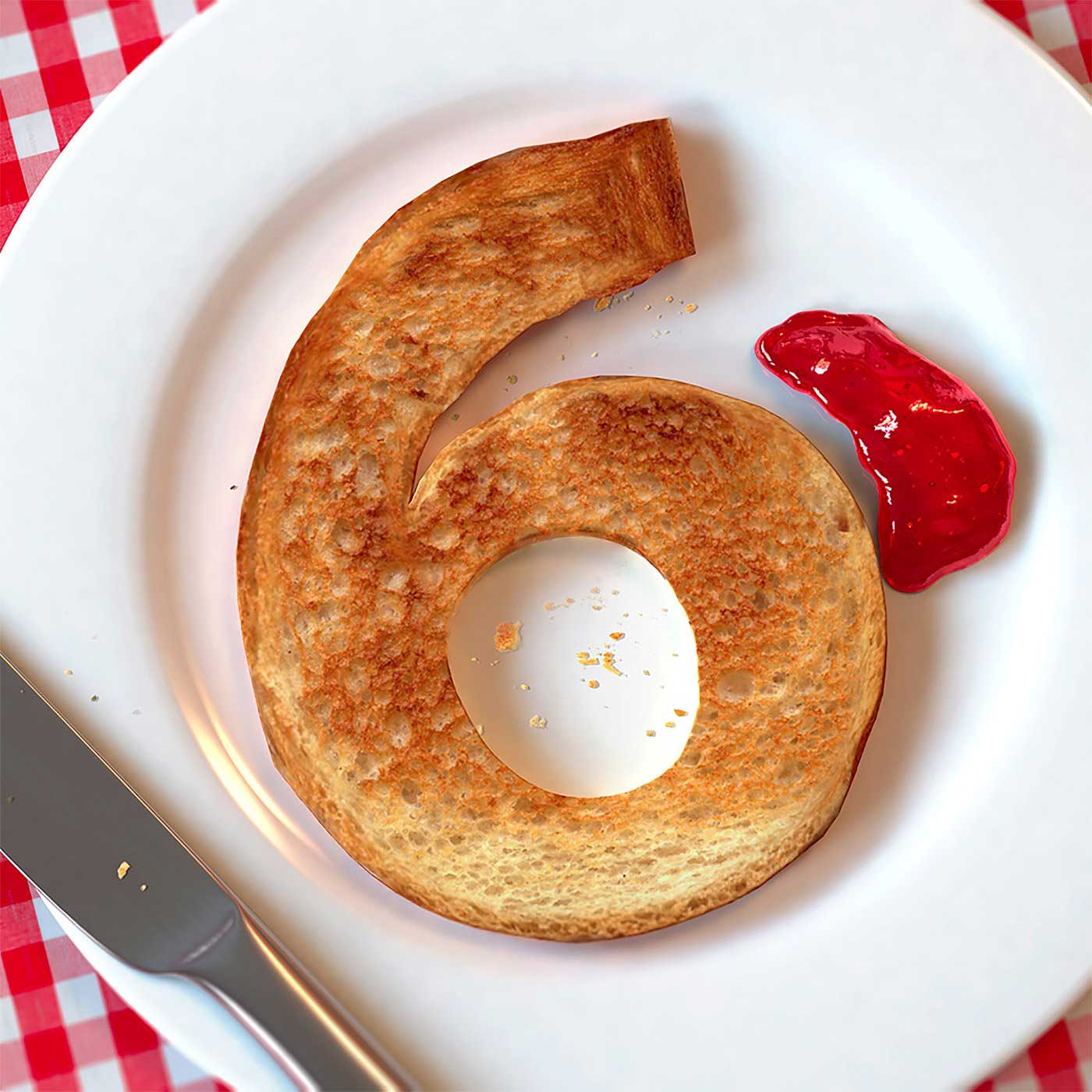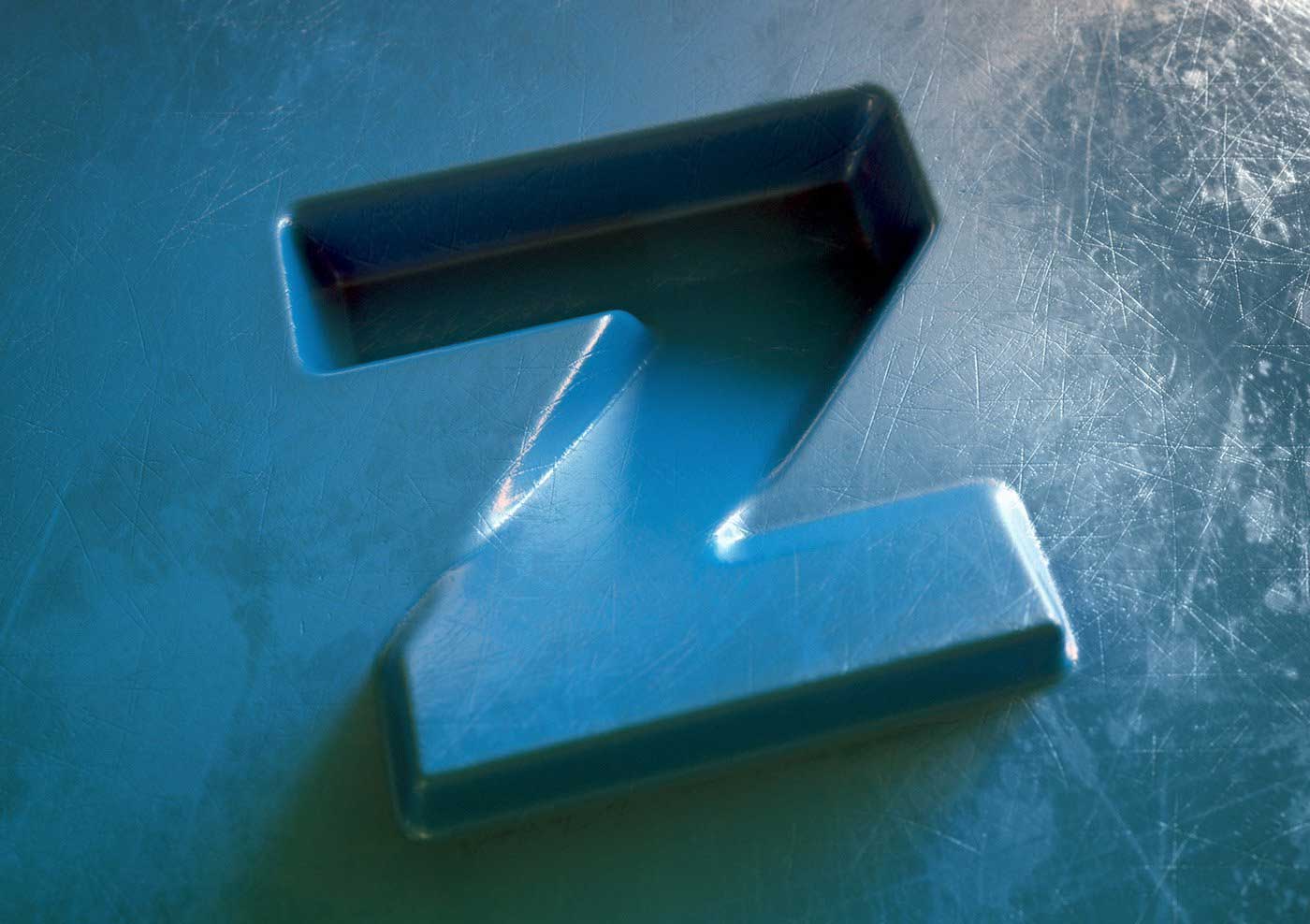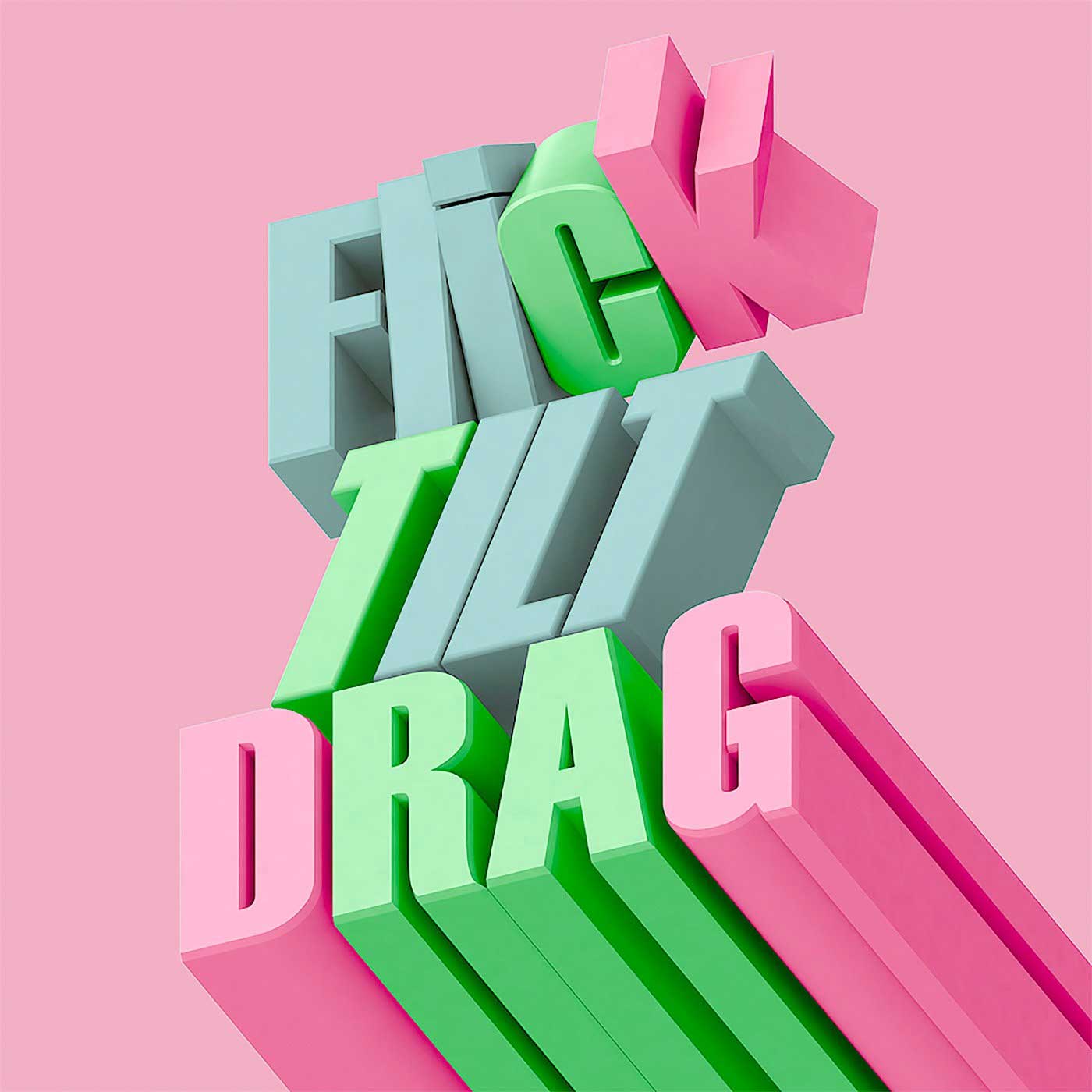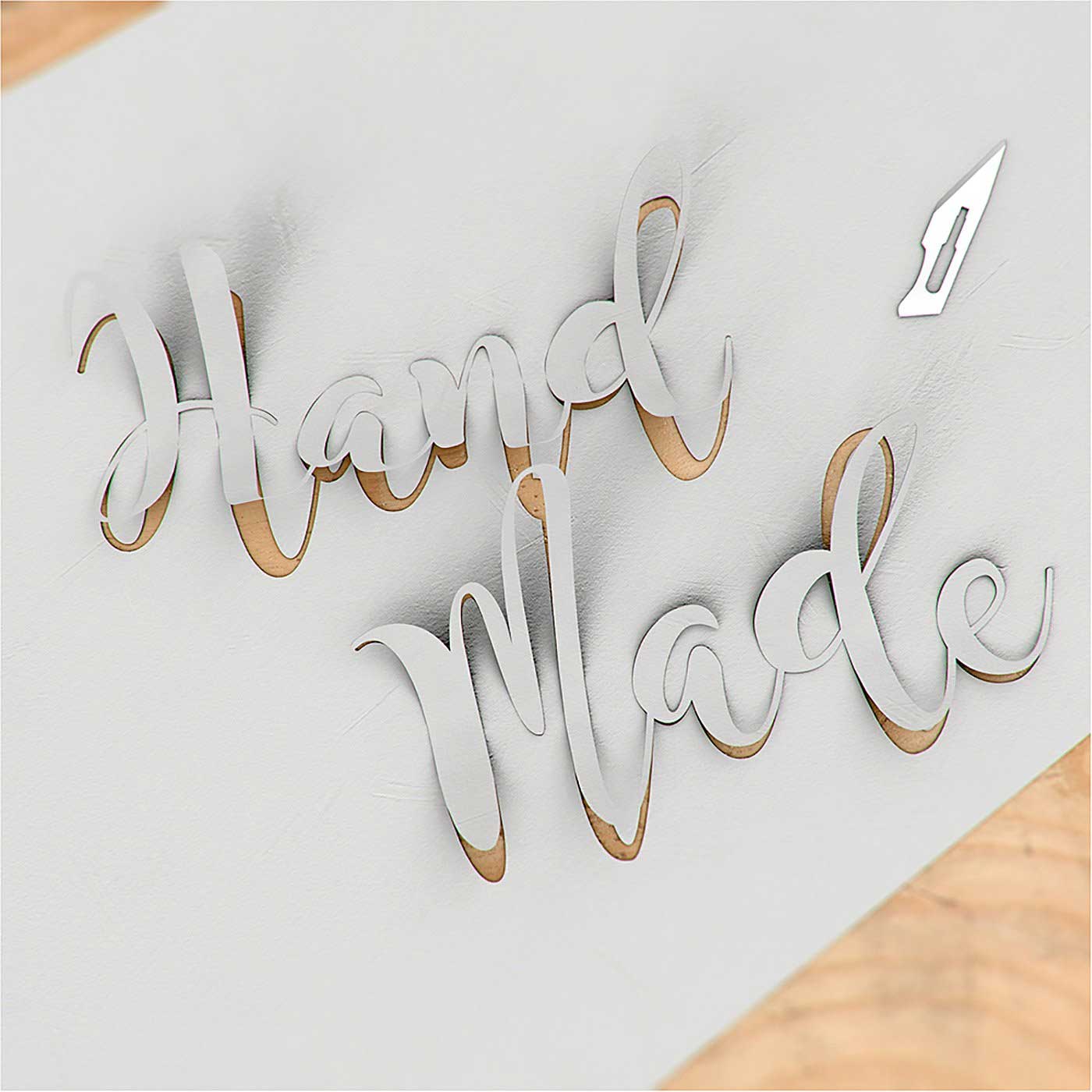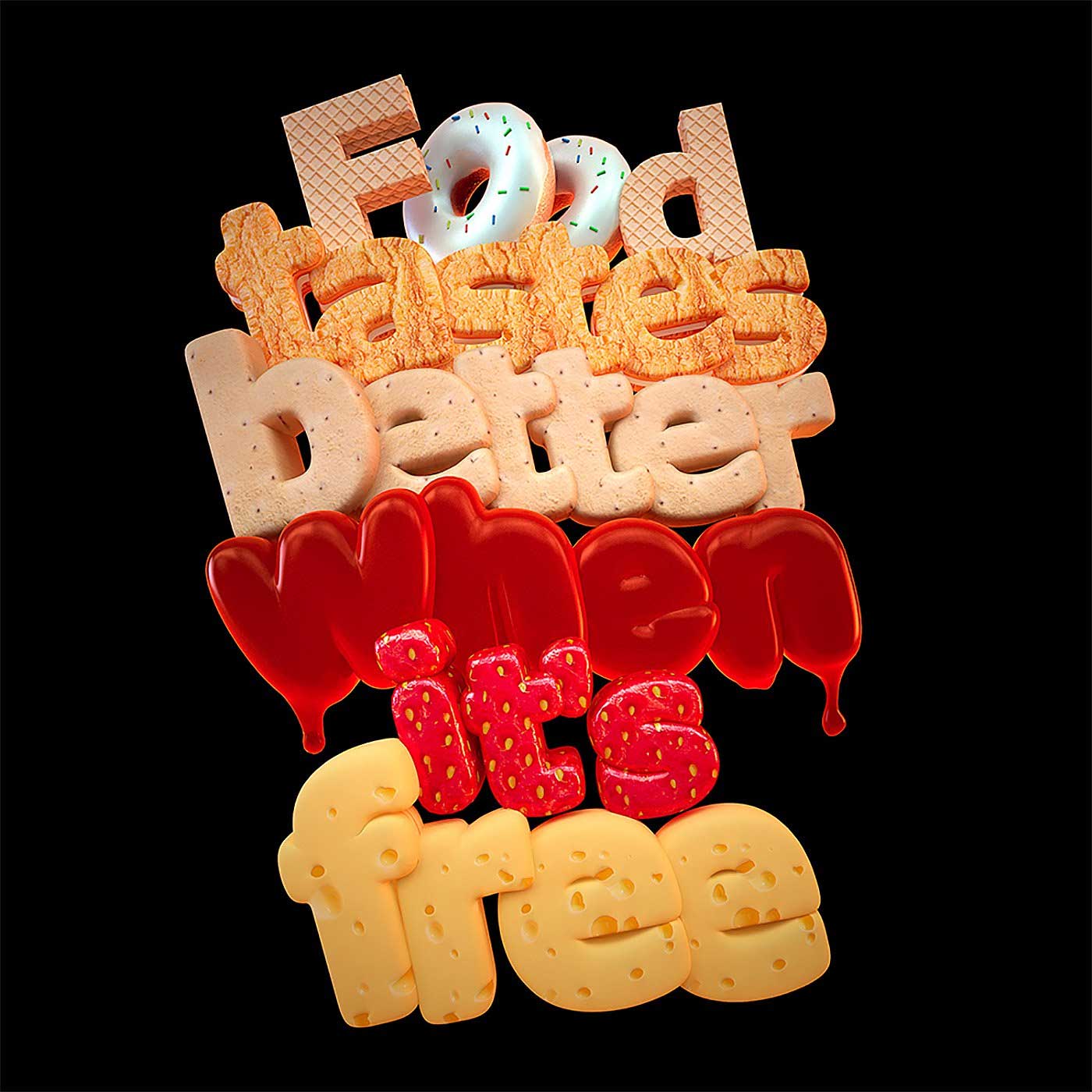
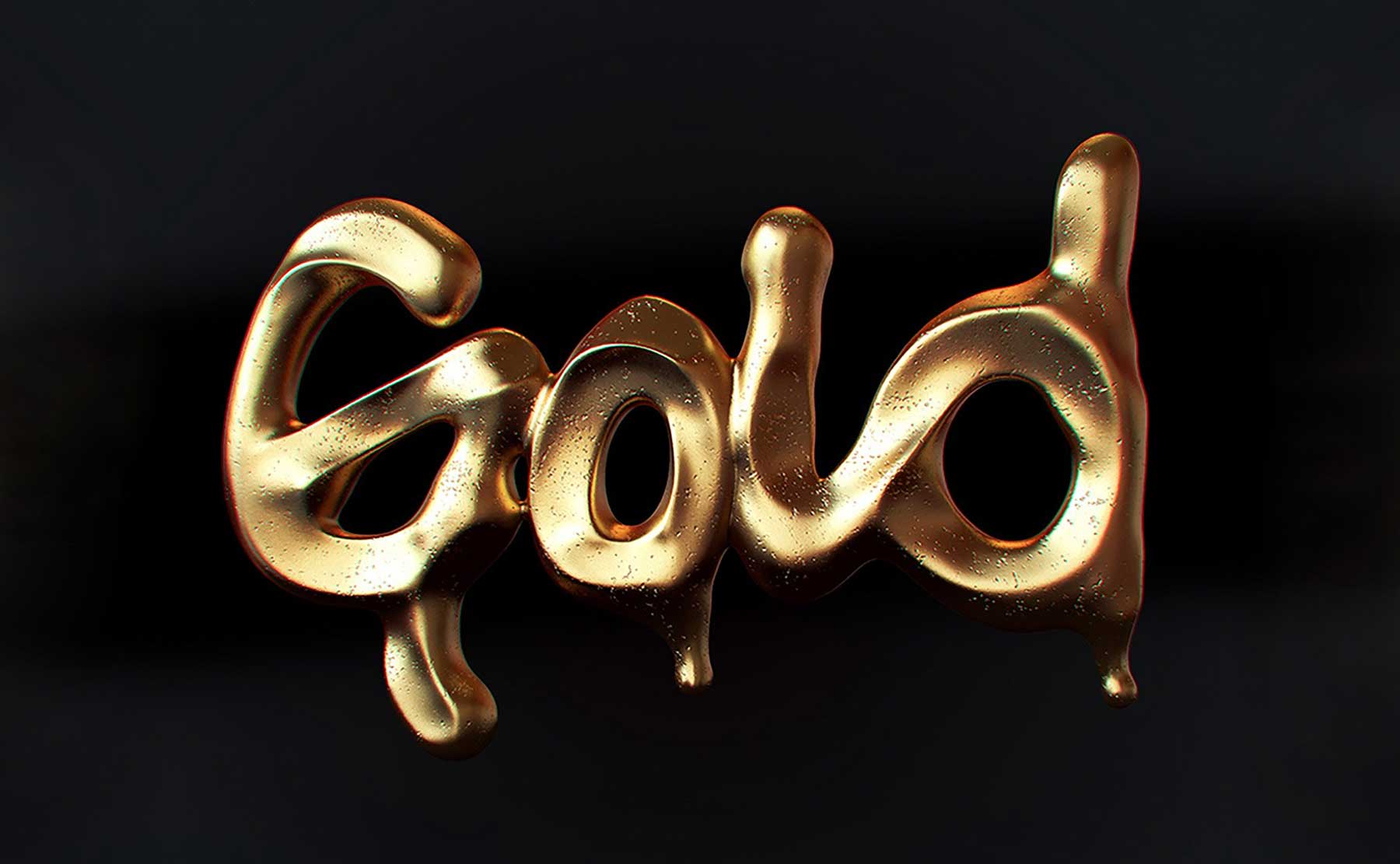
Der 3D-Designer Mat Brown aus London hat eine Reihe sehr schöner Typografie-Arbeiten erstellt. Nicht nur macht er seit Jahren bei der „36 Days of Type“-Challenge mit, auch abseits dessen liebt er das kreative Spiel mit Buchstaben und Wörtern, die am Rechner verdreht, verzogen und gefärbt werden. Hier eine kleine Auswahl für euch.
„3d Visualising, pixel pushing, skinny, English, follower of things.“